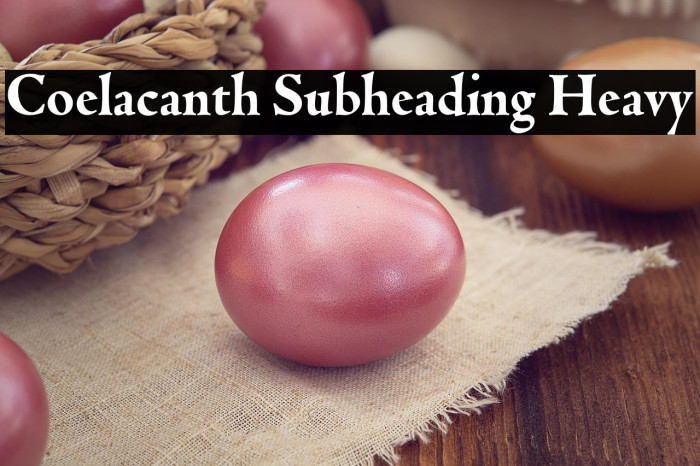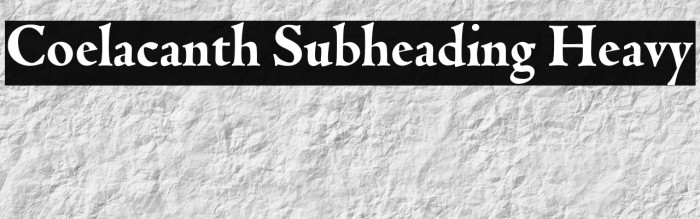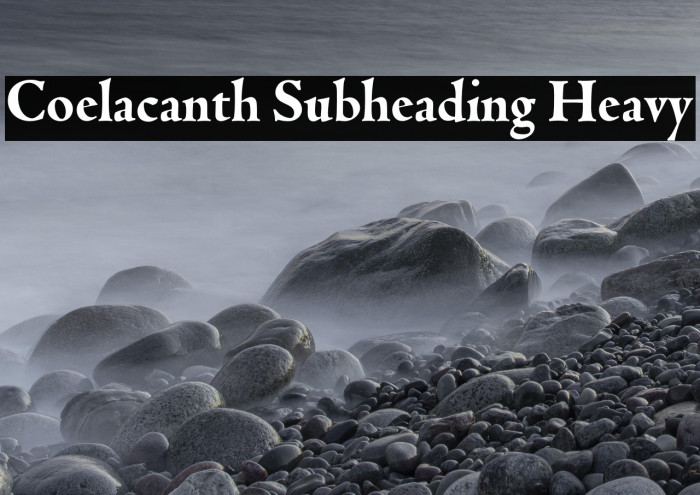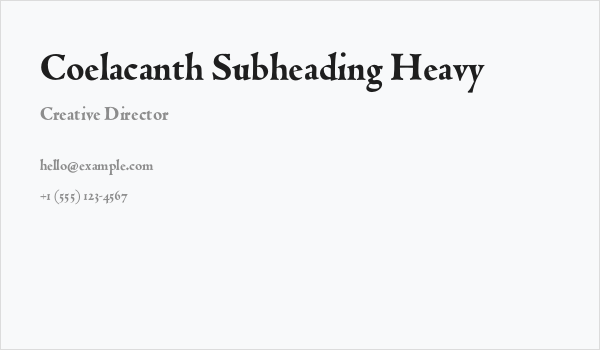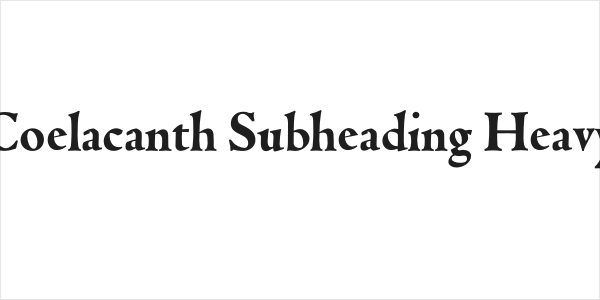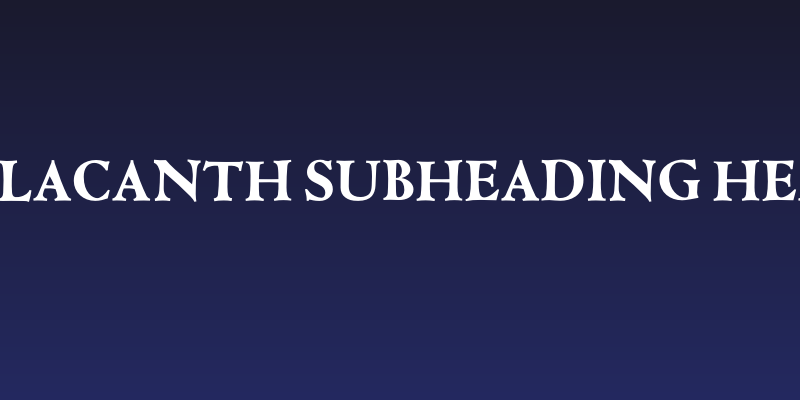
Coelacanth Subheading Heavy Font
| Proiecte propuse | Ideal for use in headlines, branding, posters, and editorial design where a strong visual impact is desired. |